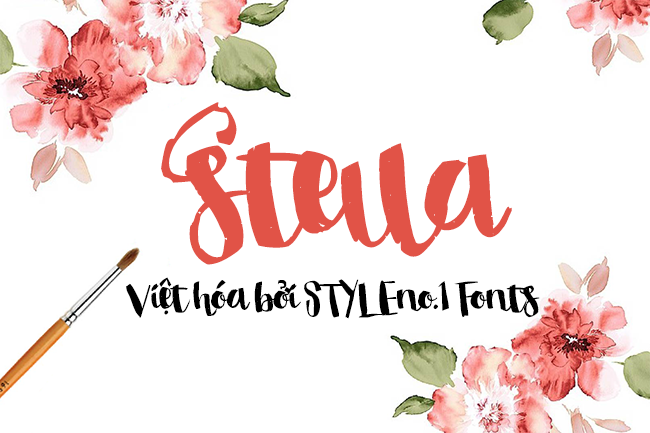
Font việt hóa SVN Stella – brush
Font việt hóa SVN Stella – brush: Nét cọ phóng khoáng cho mọi thiết kế sáng tạo
Giới thiệu về Font việt hóa SVN Stella – brush
Trong thế giới đồ họa hiện đại, việc lựa chọn một Font Miễn Phí chất lượng luôn là ưu tiên hàng đầu của các nhà thiết kế. Font việt hóa SVN Stella – brush nổi bật như một giải pháp hoàn hảo cho những ai yêu thích phong cách viết tay đầy cá tính. Đây là bộ phông chữ được chuyển ngữ sang tiếng Việt một cách tỉ mỉ, giúp người dùng dễ dàng sử dụng trong các phần mềm thiết kế phổ biến mà không lo lỗi hiển thị hay thiếu ký tự dấu đặc trưng.
Đặc điểm nổi bật của font chữ brush
Font việt hóa SVN Stella – brush sở hữu những đường nét mạnh mẽ, mô phỏng chân thực kỹ thuật vẽ cọ khô (dry brush). Các nét thanh, nét đậm xen kẽ tạo nên sự uyển chuyển nhưng vẫn giữ được độ thô ráp tự nhiên. Kiểu dáng này cực kỳ phù hợp với các bạn học sinh đang muốn thiết kế báo tường, thiệp mừng hay những poster sự kiện trường học cần sự năng động và phá cách.
Ứng dụng thực tế của Font việt hóa SVN Stella – brush
Nhờ tính linh hoạt cao, Font việt hóa SVN Stella – brush thường xuyên xuất hiện trong các bộ nhận diện thương hiệu thời trang, bìa sách hoặc tiêu đề video YouTube. Với các giáo viên và học sinh, bộ phông này có thể làm mới các bài thuyết trình PowerPoint, khiến nội dung trở nên lôi cuốn và bớt khô khan hơn. Sự kết hợp giữa nghệ thuật thư pháp hiện đại và tính ứng dụng cao giúp Stella – brush trở thành công cụ đắc lực trong mọi dự án truyền thông thị giác.